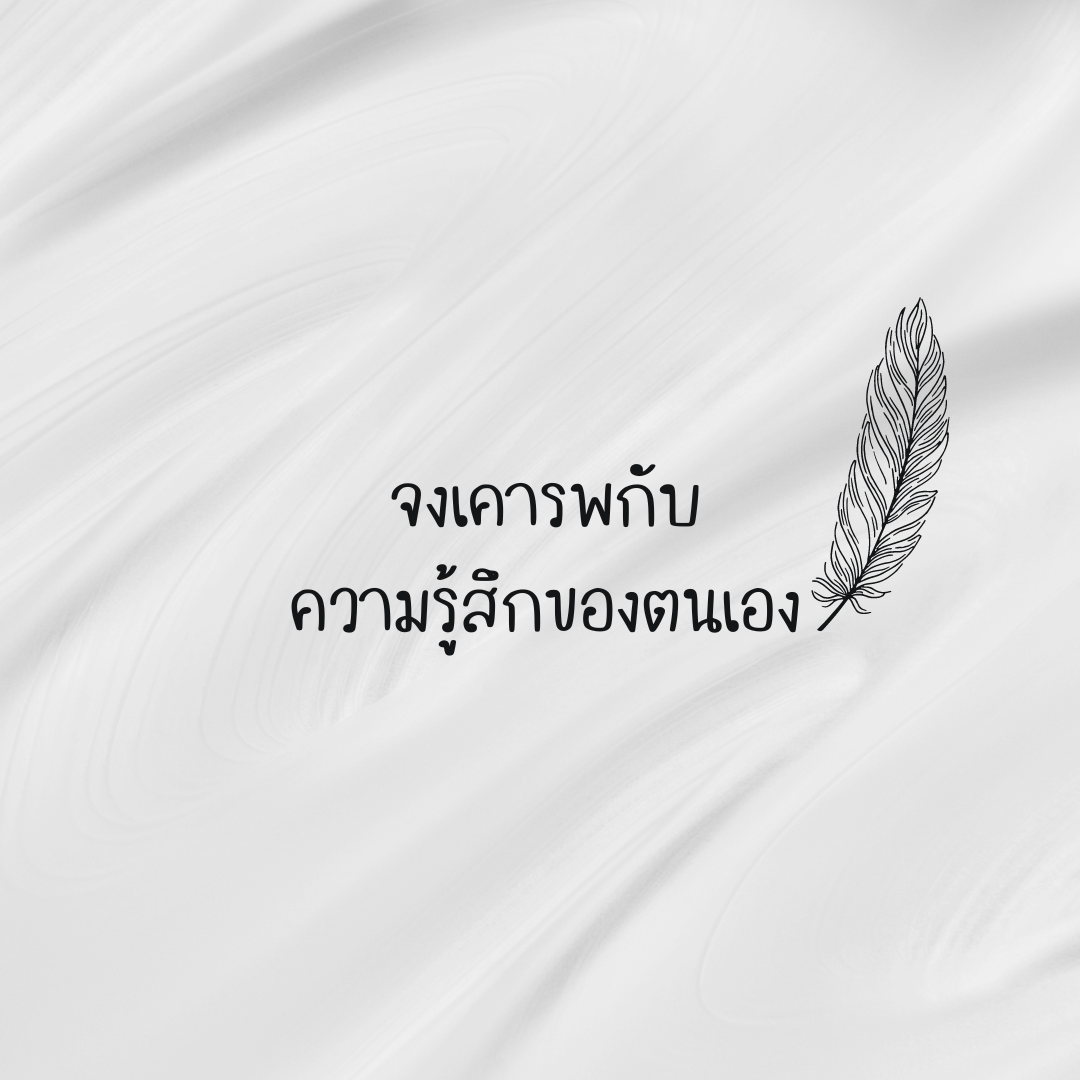
ฟอนต์ พลั้ม (Plump)
ฟอนต์ พลั้ม (Plump) ฟอนต์ที่มีเอกลักษณ์ ใช้ทำงานสไตล์น่ารักๆ จดโน้ต หรือจะทำแฟลชการ์ดก็ดูดี  แจกฟรีไปเลยเวอร์ชันทดลอง : แบบปกติ 1 น้ำหนัก ใช้ได้เฉพาะแบบส่วนตัว เช่น ใช้ในการศึกษา ใช้จด ใช้ตกแต่งสมุดโน้ตตัวเอง